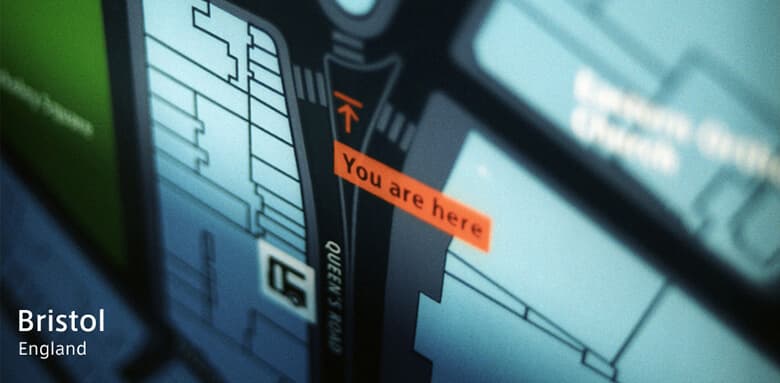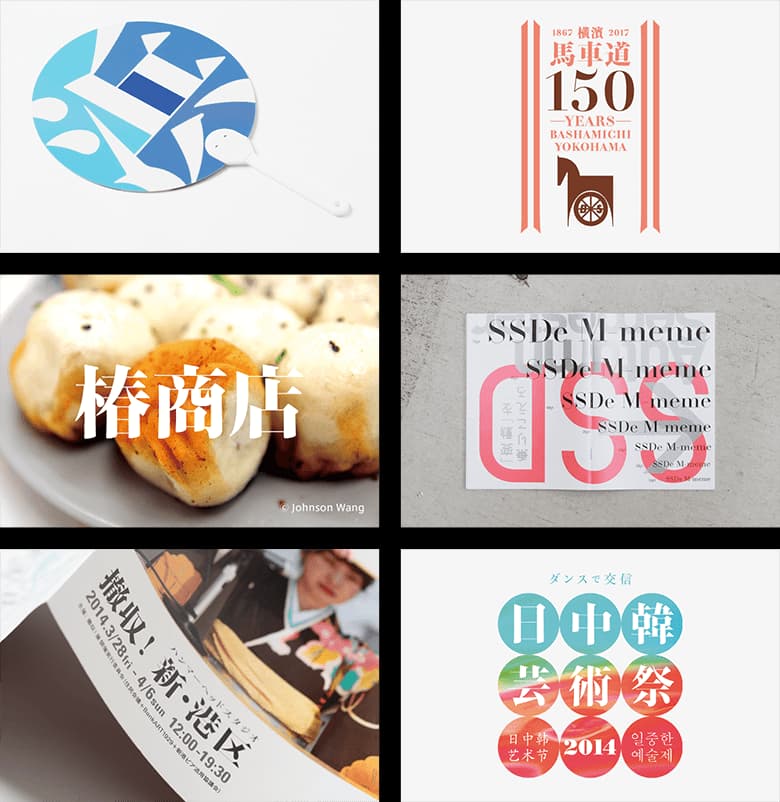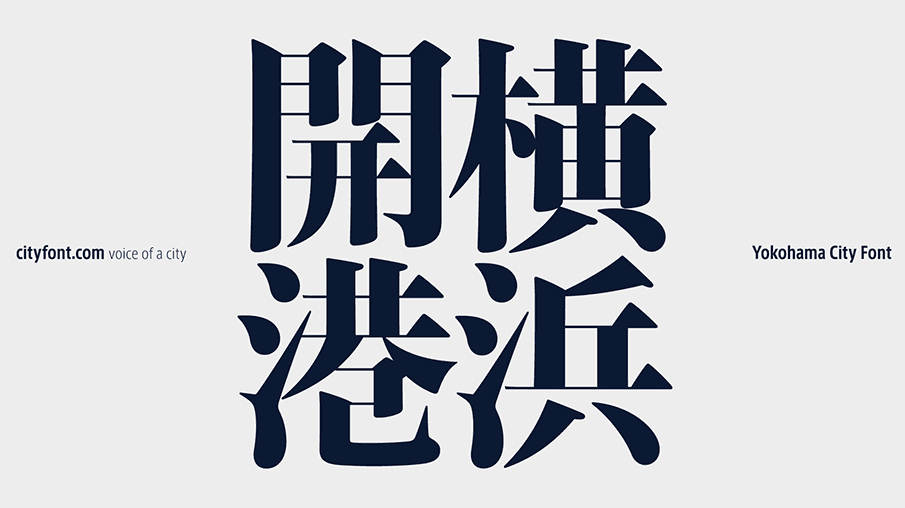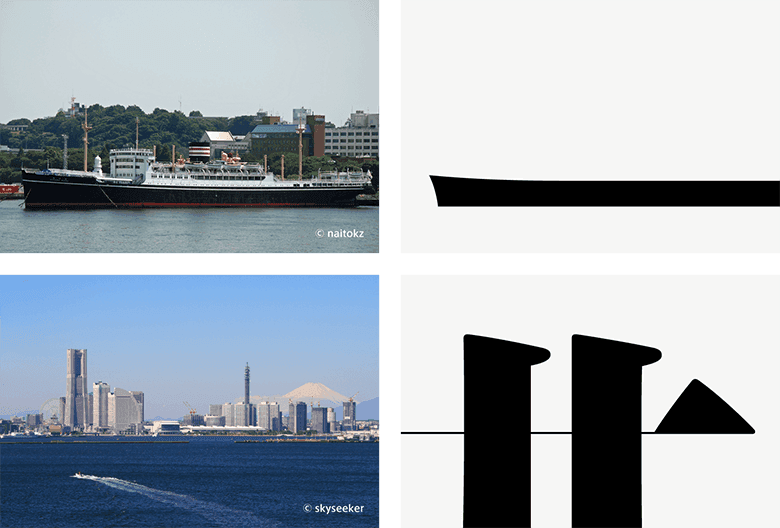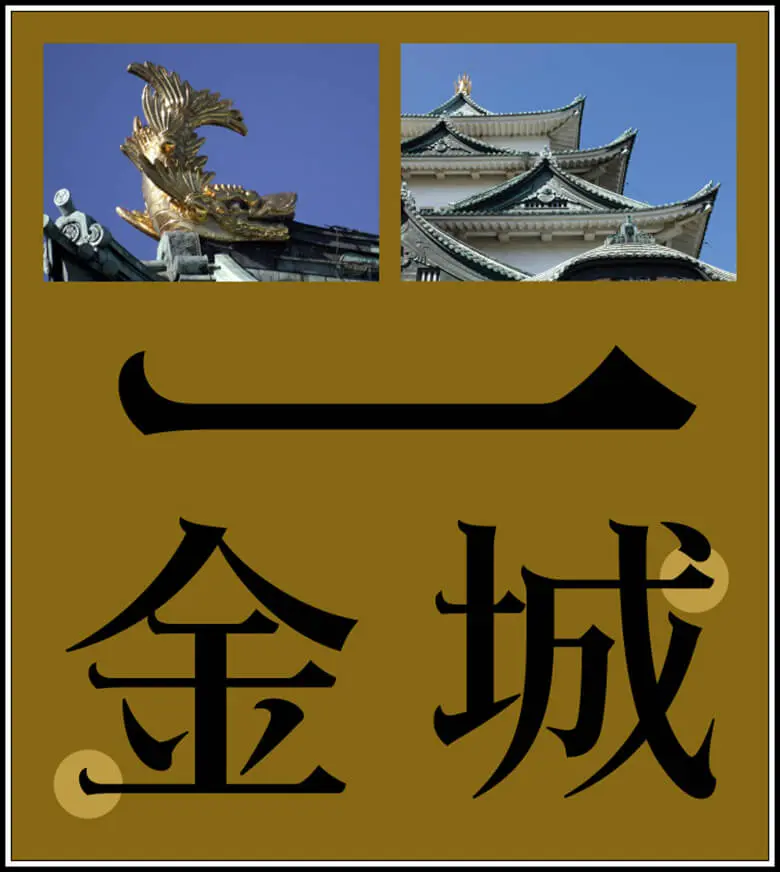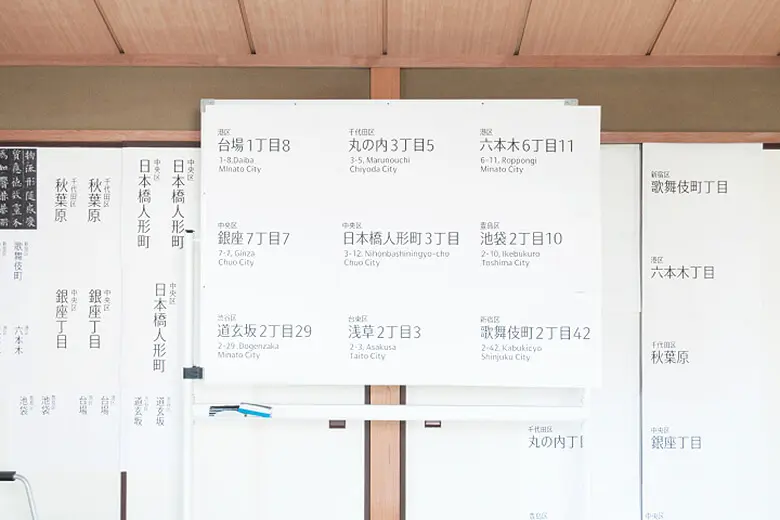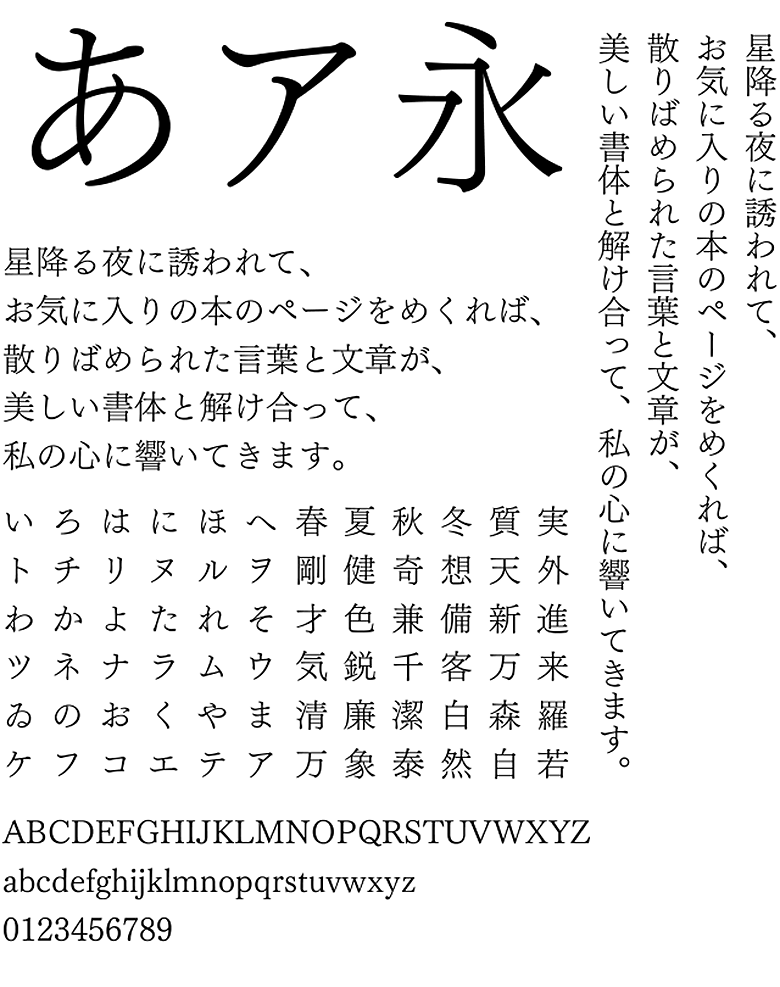
フォントで都市の価値を高める“都市フォント”プロジェクト
欧文と和文をひとつの書体ファミリーで組むための「AXIS Font」や、デジタル環境での読みやすさを追求した「TP明朝」など、時代の変化を見すえた書体開発をメインに、独自性の高い先進的な取り組みを行うType Project。
2009年より「都市フォント」の取り組みをはじめました。
それは都市が持っている独自の個性や魅力をフォントのデザインに取り入れることで、フォントを通して都市らしさを具現化するという試みです。
例えば、その都市で使用するフォントを都市フォントに統一することで、都市ブランディングのひとつとして、アイデンティティの形成や景観に貢献するツールとなることを目指しています。
世界の都市フォント
世界には都市ブランディングのためにつくられたフォントがいくつも存在しています。
例えば、イギリスの都市ブリストルで「わかりやすい都市ブリストル」を目指し開発されたのは、「Bristol Transit」というオリジナル書体。
ベルリンの地下鉄書体である長体の「Transit」を元につくられ、都市のサインシステムや路上マップ、携帯歩行用マップにも統一的に使用されています。
その他にも、イタリアのローマや韓国のソウル、フランスのトゥールーズなど、都市のブランディングやアイデンティティために書体がつくられた都市はたくさんあります。
日本での取り組み
Type Projectが2009年に立ち上げた都市フォントプロジェクトのひとつとして、名古屋をイメージした「金シャチフォント」がつくられました。
起筆部分には金シャチの反り、ウロコと呼ばれる終筆部分に名古屋城の破風と屋根の反りの形状を反映させ、名古屋文化の象徴をとり入れたフォントとなっています。
2015年には、東京の新しい街区表示板を提案する「東京シティフォント」がつくられました。
東京シティフォントは、江戸っ子と東京人に通じるさっぱりとした気質を表現した飾りのないサンセリフ体、てきぱきしている様子を表した軽めのライトウェイト(太さ)、垢抜けている様子をあらわした細身のコンデンス(字幅)、いきいきとした様子を表した抑揚のあるストロークといった特徴を持っています。
現在制作中の「濱明朝」
そしてもうひとつ、2009年から開発に取り組み現在制作中なのが、横浜をイメージした都市フォント「濱明朝」。
港の水平線やフェリーを表すなめらかなカーブをほどこした横画と、海上から望む建築群に見立てた力強い縦画が特徴のフォントです。
試作段階ながら、濱明朝は横浜の企業の商品開発やイベント時のポスター、お店のロゴタイプとしてなど、使われる機会が増えてきています。
フォントで都市を表現する
福岡のフォントベンダーFONTWORKSがつくった「筑紫書体」というフォントがあります。
これまでとは一線を画した特徴的な形状で、細部までこだわりがつめ込まれた筑紫シリーズは、デザイナーの中にもファンが多いフォントです。
都市の特徴をあらわす“都市フォント”という概念からつくられたわけではありませんが、福岡でつくられたフォントということで福岡の古い名称“筑紫”という名前を冠しています。
“筑紫”という名称を広く浸透させたフォントという意味では、福岡という都市のブランディングに一役買っているのかもしれません。
フォントという切り口から都市を表現するこの試み、今後も各地に広がっていくと面白いですね。